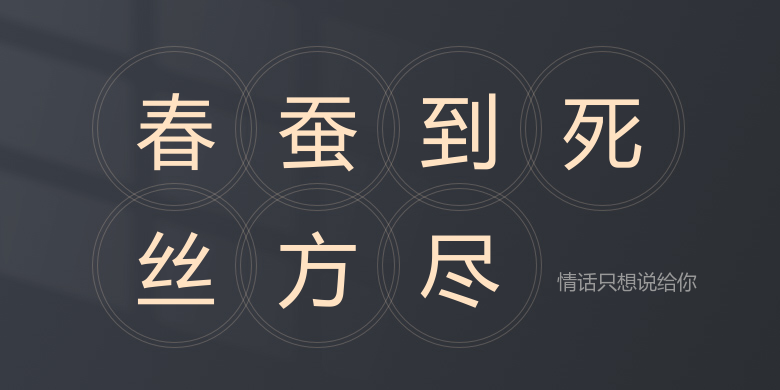
情话只想说给你
情话只想说给你,这款字体结构工整、笔画清晰,兼顾美观与易读性,适用于标题、正文、海报、包装、LOGO 等多种场景。字形优雅稳定,风格百搭耐看,适配日常排版与创意设计,让文字呈现更舒适、更具质感。情话只想说给你一笔一画,皆是细节,以均衡的比例、流畅的线条打造舒适视觉体验,字形端正大气,风格简约现代。无论是商业设计、品牌宣传还是日常排版,都能轻松驾驭,让文字更有格调与力量。情话只想说给你字体下载。